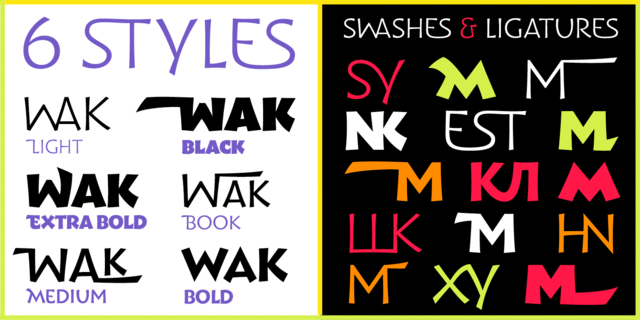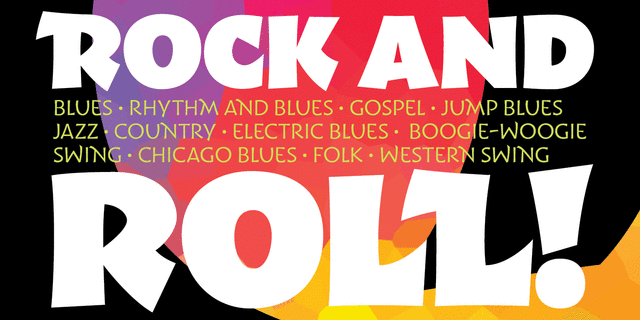
Wak — «живой» гротеск на основе каллиграфии. В его рисунке простота и плавность форм сочетается с остротой и внезапностью деталей. В шрифте шесть начертаний от светлого до сверхжирного, с большим количеством альтернативных знаков, дополнительных лигатур и начальных и конечных форм с росчерками. Строчные знаки повторяют рисунок прописных. Шрифт предназначен для коротких надписей и небольших фрагментов текста и адаптирован для использования на экране. Wak разработан Виктором Фицнером и расширен по составу знаков Александром Любовенко. Шрифт выпущен компанией ПараТайп в 2018 году.